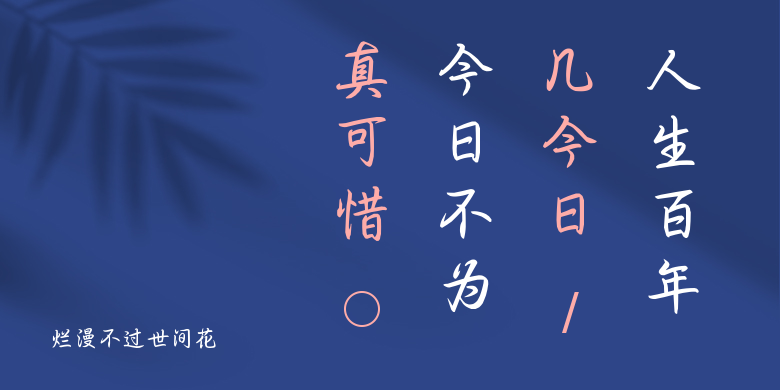
烂漫不过世间花
烂漫不过世间花,这款字体结构工整、笔画清晰,兼顾美观与易读性,适用于标题、正文、海报、包装、LOGO 等多种场景。字形优雅稳定,风格百搭耐看,适配日常排版与创意设计,让文字呈现更舒适、更具质感。烂漫不过世间花一笔一画,皆是细节,以均衡的比例、流畅的线条打造舒适视觉体验,字形端正大气,风格简约现代。无论是商业设计、品牌宣传还是日常排版,都能轻松驾驭,让文字更有格调与力量。烂漫不过世间花字体下载。